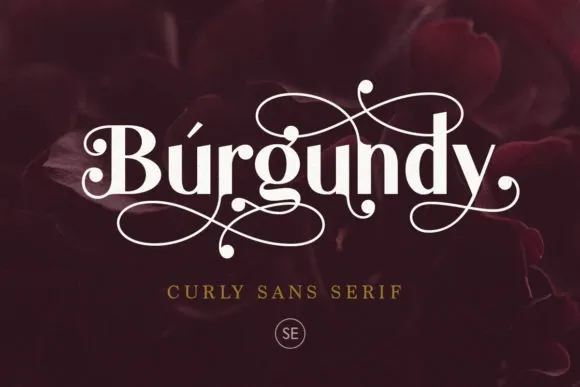
A fonte Burgundy é uma escolha perfeita para aqueles que buscam uma tipografia moderna e elegante para suas criações digitais. Ela foi criada pelo designer Saridezra e é baseada em tipo de mão sem serif, oferecendo um visual clean e versátil. Os traços curvados e delicados da fonte adicionam um toque sofisticado que irá destacar sua apresentação ou logotipo ainda mais. Ideal para uso em cartões de casamento ou celebrações, a Burgundy também suporta múltiplas línguas e já está PUA (Unicode Precomposed Unicode Alternatives) codificado, tornando-a uma fonte versátil e conveniente para designers de todos os níveis.